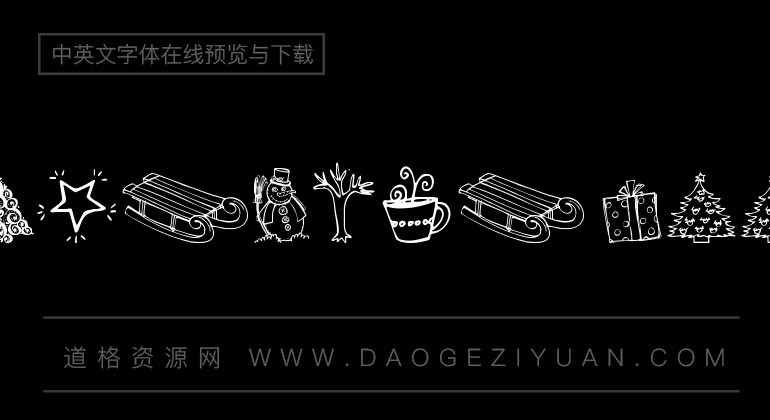
Janda Christmas Doodles Font 是一种装饰性的字体,适用于圣诞节主题设计、贺卡、海报、宣传册等等。 此字体的字母有着圆润的外形,同时还包含了丰富的圣诞元素的插图,如圣诞树、圣诞袜、礼物、圣诞帽等等,让你的设计更具有节日气氛。此字体还包含了一些有趣的符号,如雪花和星星。 Janda Christmas Doodles Font 支持多种字体格式,包括 TrueType、OpenType 和 WebFonts,可以在 Windows 和 Mac 操作系统上使用,并且可以与 Adobe Creative Suite 等软件兼容。内容介绍
Janda Christmas Doodles Font是一款非常不错的手写艺术字体,具有很好的视觉感,适合于文化类的宣传设计、商业类品牌的广告和产品包装设计以及个性化文字排版等较多场景。